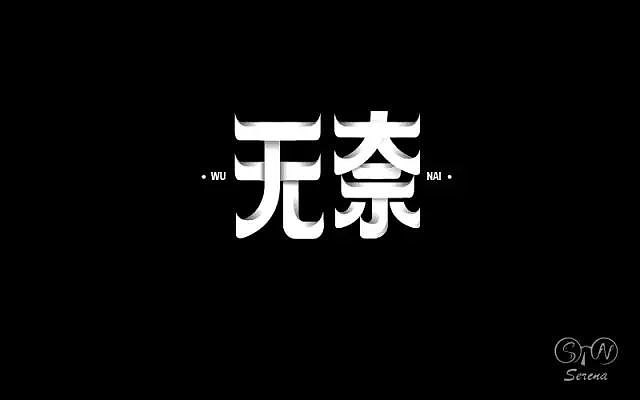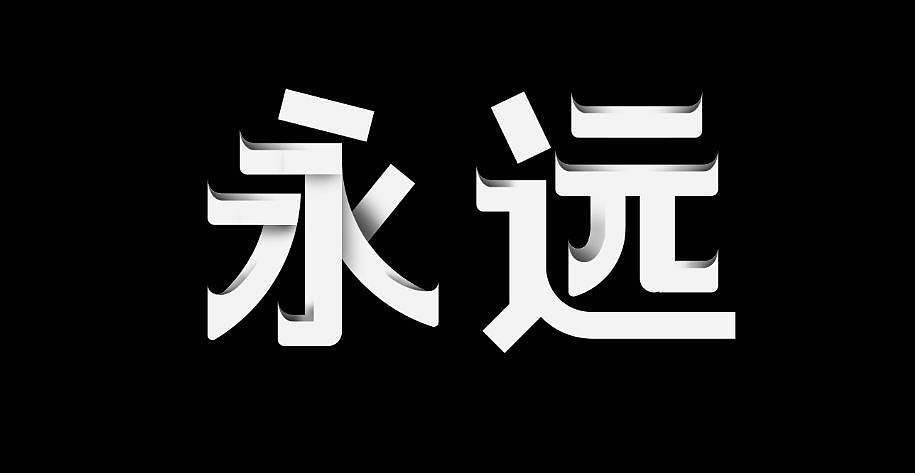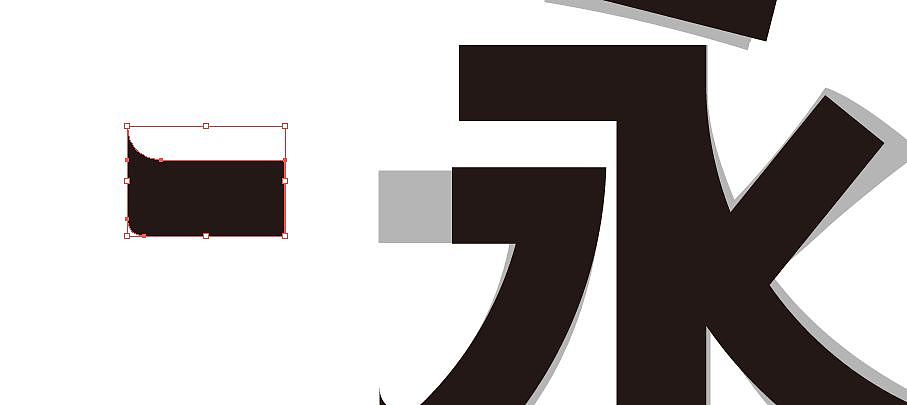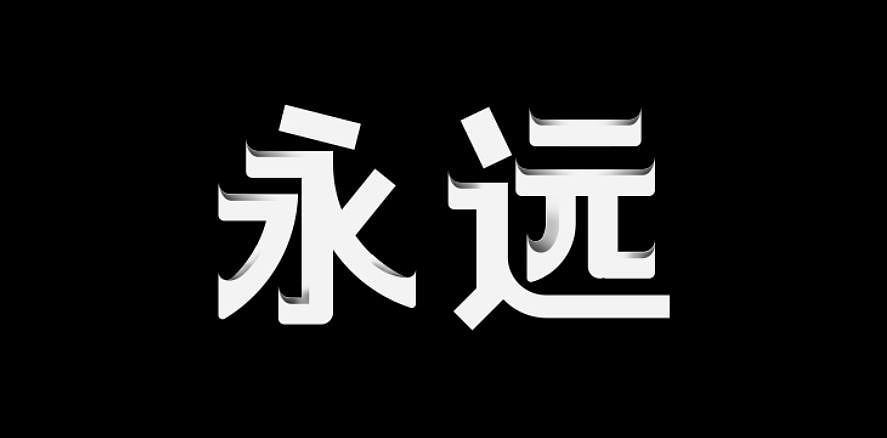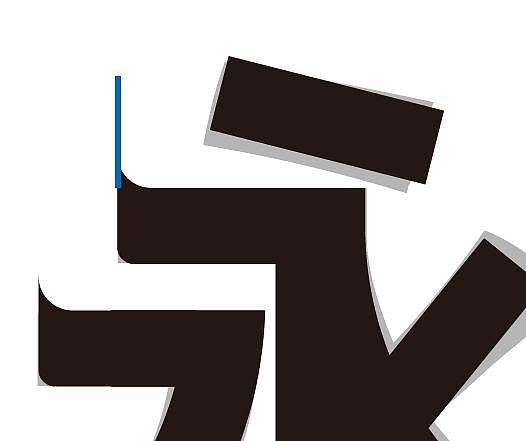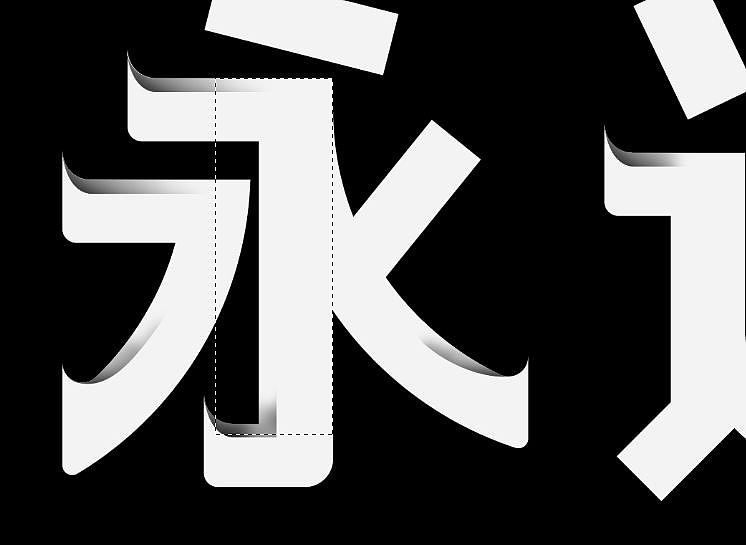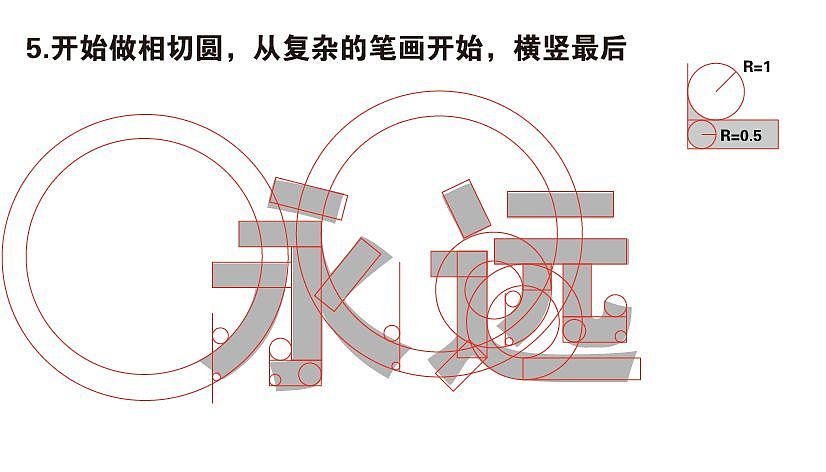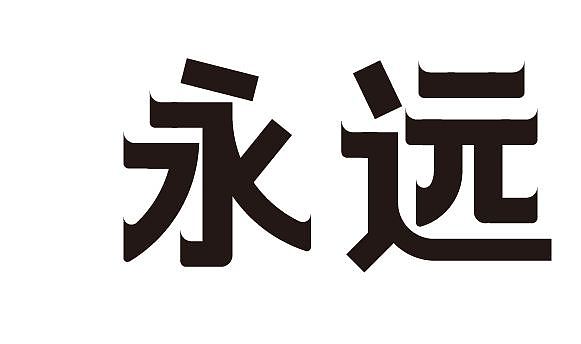
字体设计之底描法
今天在字体界发现了一枚字体觉得不错,不知道我写的教程原作者会不会喷我,先说对不起啦,我把自己想法写出来,制作过程应该是大相径庭的。请看大屏幕:好可惜,水印上的名字看不大清楚,有人认识么~其实别管他啦,开始我们造字之旅。
分析:“无奈”二字,在笔画粗细来看,应该就是黑体,但是又不知道是何种黑体,只能在字体库找咯。再者这两字的特点(除去质感)在于末端的造型:
这种倒角方式是外圆是内圆的半径的两倍,再往下看。
1.寻找好字体,我觉得方正的大黑简体挺般配~
2.重新构造,如图:以前我们造字之前需要建造田字格,但是底描法不同,在它下面有个原始字体约束,在重心方面我们就不需要过多去考虑了。
3.由简单的笔画开始,横竖点那些,横竖不一定要粗细相同,看情况而定。
4.这种一般都是用圆利用锚点去捕捉对齐
5.还记得上次推荐的那个插件么(subcribe),这里就需要倒圆角了。像下图右上角一样的圆形比例去倒角。
6.然后使用快速填色工具填色:
填色完毕,拼合透明度,使用联集命令:
我们会发现这个字体造型跟原来的还不一样,横方向的末端造型还没出来,其实最后挺简单的,只需要弄一个然后复制即可:
就是把原来的横方向往里面缩小一点,然后把准备好的覆盖上去就OK啦~其他也一样,不过这里注意,覆盖后,笔画的长度要和原来的一样,不然字体结构就要被我们破坏了。
好了基本差不多了,我们转到 PS 里面做字体质感:
1.使用钢笔工具,按照原来字体的质感模拟画出填色区域:
2.然后使用画笔工具进行涂抹,画笔透明度改为40%,在圆角处要深一点:
然后通过复制,把它覆盖到其他笔画上:
横向的做好了,那些其他的同样做法,只不过不能复制了,因为他们结构不同,自己慢慢用钢笔勾勒出填色区域,再用画笔涂抹吧:
最后一步,就是让笔画之间呈现出叠加结构,选好选区,也是用画笔涂抹即可:
最后涂抹成这样、大功告成~